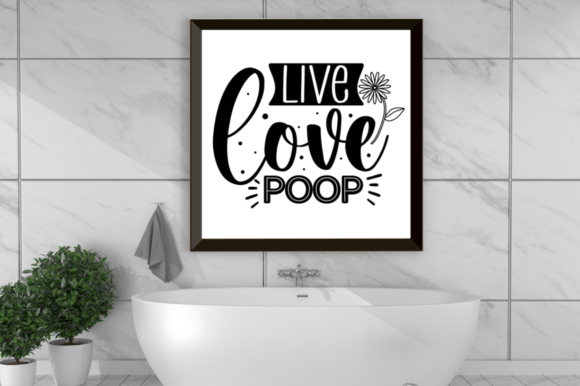
Live Love Poop SVG
Trovare i giusti elementi di design può essere difficile, ma Live Love Poop SVG offre una collezione eccezionale che eleva istantaneamente il tuo lavoro.
Realizzato con precisione, Live Love Poop SVG fornisce vettori puliti, tipografia fluida e una licenza commerciale per la massima tranquillità.